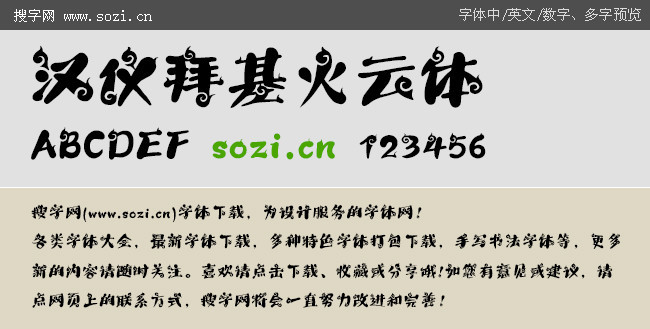
漢儀拜基火云體
搜字網(wǎng)給大家提供一款漢儀拜基火云體中文字體下載。漢儀拜基火云體是一款自帶火焰特效的藝術(shù)字體,全新的設(shè)計(jì)帶你領(lǐng)略全新的字體內(nèi)容,超強(qiáng)設(shè)計(jì)感,筆鋒奇特,讓字體帶你一起發(fā)現(xiàn)更多的不同!適合兒童卡通設(shè)計(jì)、海報(bào)設(shè)計(jì)、網(wǎng)頁(yè)標(biāo)題設(shè)計(jì)等應(yīng)用。(本字體為個(gè)人非商用版,如需要商用請(qǐng)聯(lián)系漢儀公司購(gòu)買(mǎi)版權(quán))